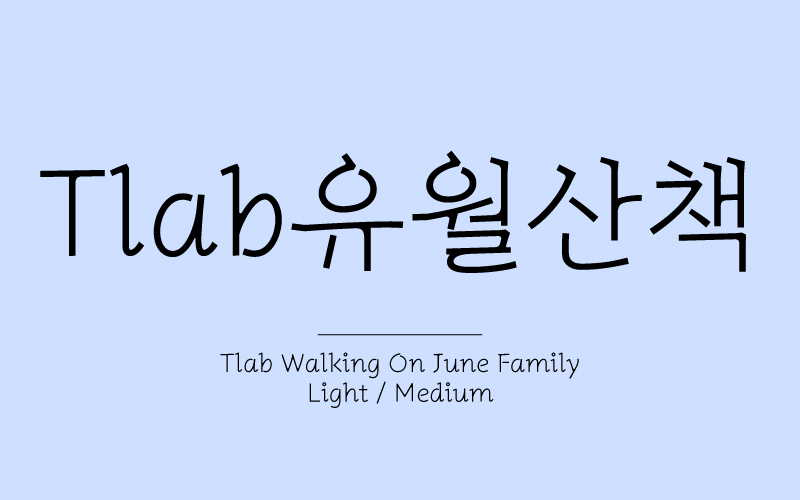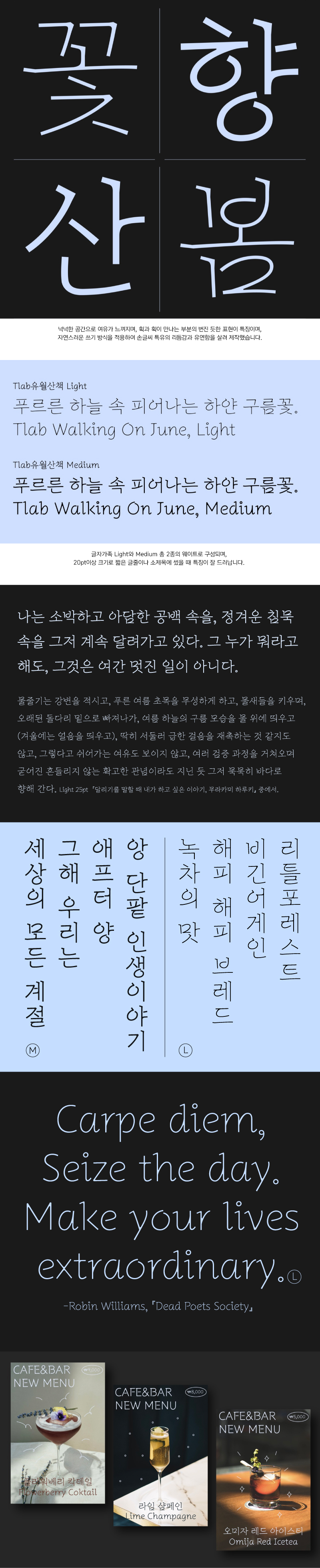
Tlab유월산책
2 종 - Medium, Light넉넉한 공간으로 여유가 느껴지며, 획과 획이 만나는 부분의 번진 듯한 표현이 특징입니다. 자소 ‘ㄷ, ㅁ, ㅂ, ㅇ, ㅎ’에 자연스러운 쓰기 방식을 적용하여 손글씨 특유의 리듬감과 유연함을 살려 제작했습니다.
폰트구성 | 한글 2860자/라틴 94자/ks code 약물 986자 |